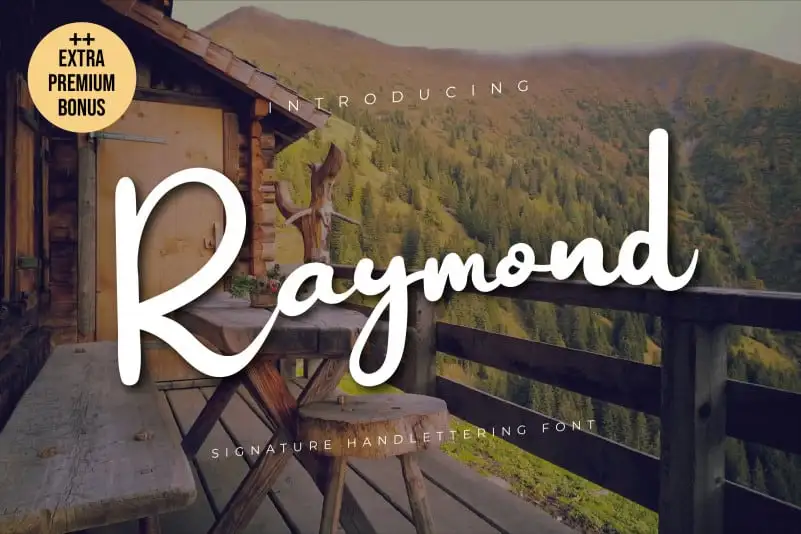
Raymond Script Font – Download Grátis
A ‘Raymond Script Font’ é uma delícia para aqueles que buscam elegância natural em suas criações digitais. Simplificada na essência do estilo manuscrito, essa fonte é a escolha perfeita para quem deseja um toque sofisticado e contemporâneo nas suas letras. Seu charme clássico mantém sua influência tipográfica enquanto também se apresenta como fresca e vivida. A sua versatilidade torna-a uma fonte indispensável tanto para aqueles que procuram estilos arrojados, quanto para designers atentos a detalhes. Perfeita para letras de boletins ou títulos, ela é igualmente adequada para criações em materiais de escritório e cartões personalizados. Na categoria dos fontes script, ‘Raymond Script Font’ não apenas oferece beleza, mas também uma graça que enriquece sua utilização. Seja você um artista digital experiente ou iniciante, essa fonte estará sempre pronta para ajudá-lo a capturar nuances e sentimentos em suas criações digitais.